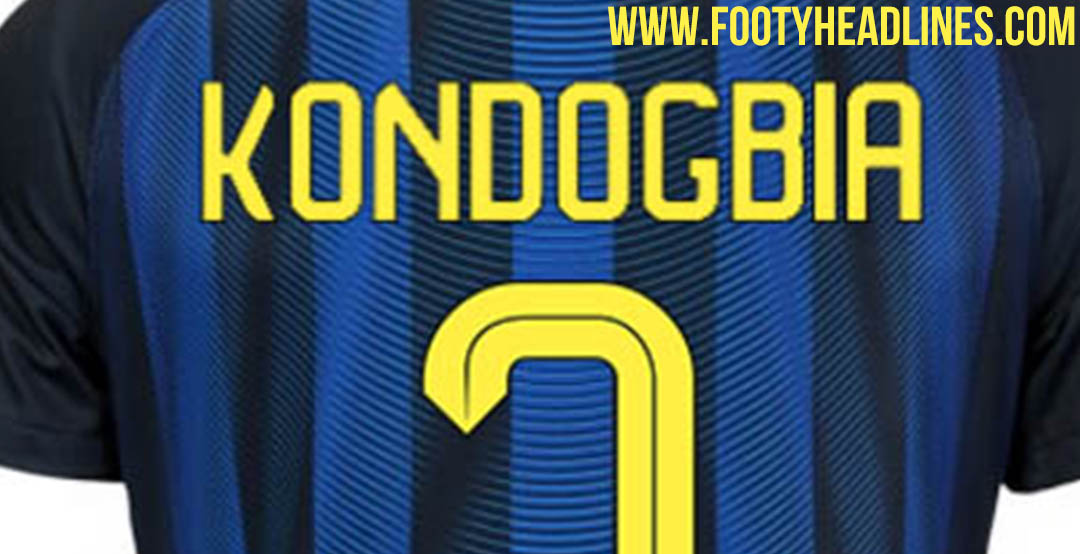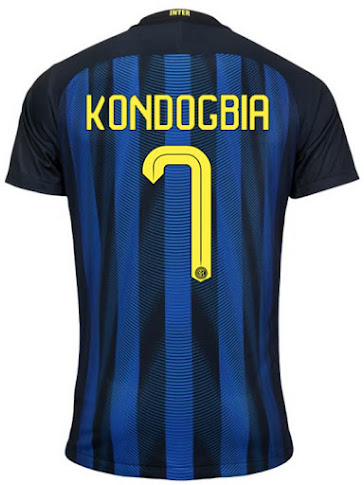
Inter 16-17 Trikot-Schriftart enthüllt
Update: Nike hat die neuen Inter-Trikots für die Saison 2016-17 enthüllt. Und da die gelben Details beim Heimtrikot hinzugefügt wurden, sind die neuen Inter Spielernamen und -nummern jetzt auch gelb und nicht weiß. Die Schriftart ist identisch - abgesehen von der Farbe.
Das neue Inter 15-16 Trikot, das früher in dieser Woche vorgestellt wurde, bleibt Inters Traditionen treu - inspiriert vom 1990-91 Inter-Trikot, mit dem der UEFA Cup gewonnen wurde. Mit dem neuen Inter 2015-16 Trikot hat Nike auch eine neue Schriftart für die Spielernamen und -nummern auf der Rückseite eingeführt.
Inter 15-16 Trikot-Schriftart
Diese Bilder zeigen das neue Inter 2015-16 Trikot mit der neu entworfenen Inter-Schriftart für Icardi und Kovacic.
Die neue Inter 15-16 Trikot-Schriftart, die ein eckiges Grundgerüst mit runden Ecken und dreieckigen Formen an den Enden kombiniert, hat ein großartiges Design.
Das Innere der Inter 15-16 Trikot-Nummern weist eine blaue Linie als auch ein einfarbiges, blaues Inter-Wappen auf.